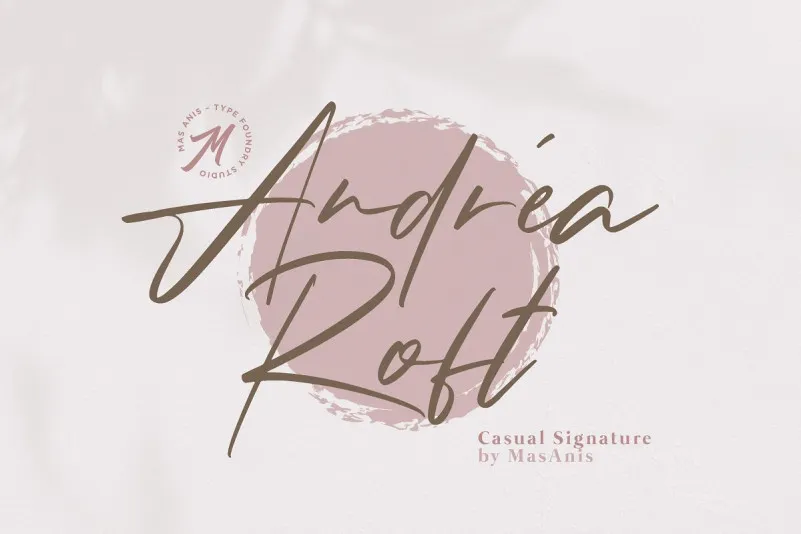
Andrea Roft Script Font – Download Grátis
A Andrea Roft Font é uma seleção elegante para quem busca um touch casual e sofisticado nas suas criações digitais. Desenvolvida pelo designer 1001fonts, essa tipografia script é perfeitamente adequada para uso em logotipos, convites, cartões de papelaria, decoração nupcial, postagens nas redes sociais, anúncios, embalagens de produtos, designs de produtos, rótulos, fotografia e até mesmo watermark. Suas linhas finas e sua feminilidade clássica fazem dela uma opção ideal para um amplo espectro de aplicativos digitais. O designer também compartilha essa fonte com o público em seu formato mais conhecido TTF e OTF. Uma das marcas principais características desta fonte é a sua aparência handwritten casual, que permite um toque natural às suas criações, tornando-a perfeita para estilos de design de produtos e moda. Além disso, essa fonte será uma grata surpresa para os criadores digitais, pois oferece tanto o TTF quanto o OTF, permitindo maior flexibilidade no processamento da fonte em diferentes plataformas. Para quem quer criar designs elegantes com um toque de casualidade, a Andrea Roft Font é certamente uma opção a ser considerada. Sucesso na sua próxima criação digital!